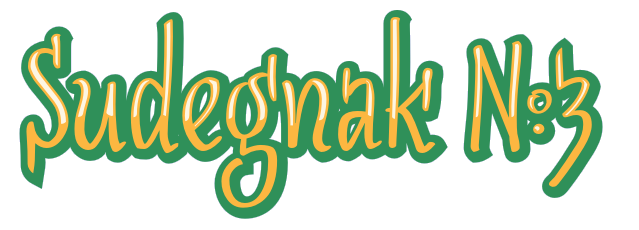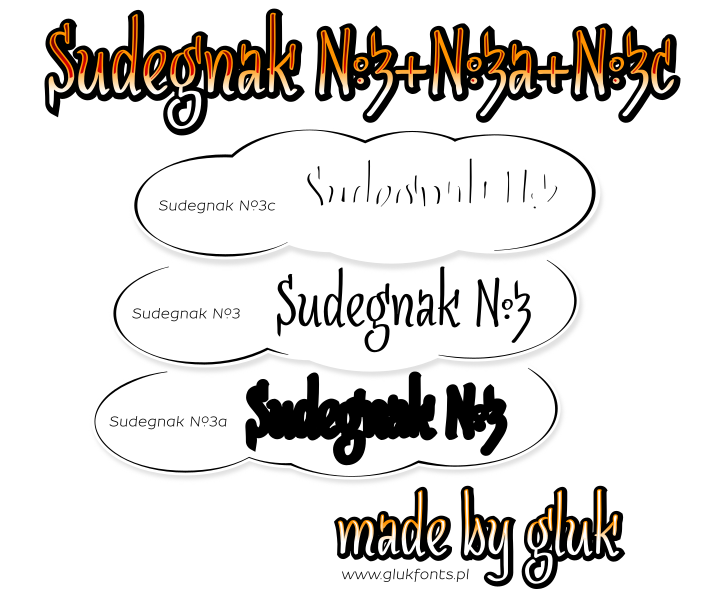
Schrift mit integriertem Hintergrund (oder kräftiges Outline) für gute Lesbarkeit auf verschiedenen Hintergründen?
Ich suche eine Schriftart, die Ich in einer Bildbearbeitung ohne der Möglichkeit des aktivierens von Hintergrund ("Marker") einsetzen kann.
Vor verschiedenen Hintergründen. Z.B. ein "Bild" (Raum), wo ein Pixel ein cm ist, liegt ein Teppich im Raum (Draufsicht in den Raum).
Z.B. ein creme-Gelb-Brauner Orient-Teppich Da finde Ich keine Farbe, am ehesten noch reines Gelb.
Eine für geringe Auflösungen gut lesbare Schrift inkl. eingebautem Hintergrund wäre eine Lösung.
Was gibt es da? Auch Freie?
Wenn möglich, inkl. eckigen Klammern, diesen Pfeil-Dreiecken etc.. Aber notfalls nehme Ich diese Symbole aus einer anderen Schriftart.
So etwas gibt es als Schrift überhaupt nicht, da normale Schrift-Fonts ja nur die Außenkontur der einzelnen Glyphen beschreiben, die dann von der Anwendung mit der gewünschten Farbe gefüllt werden. Viele Grafikprogramme bieten jedoch die Möglichkeit, der Schriftart auch eine Kontur, oder auch ein Füllung zuzuweisen. Das ist aber keine Sache der Schrift.
seit Windows8 hat Microsoft ein neues Font-Format für Emojis eingeführt, hier sind farbig definierte Schriften durchaus möglich, da hier Microsoft einem Aufsatz auf das vorhandene OpenType-Format mit einer neuen OpenType-Table gemacht hat, indem zur Grundglyphe, die in Anwendungen ohne Farb-Unterstützung (also der großen Mehrzahl an Text- und Grafikprogrammen) dann dargestellt wird (in schwarz oder einer gewählten Schriftfarbe) und weiteren Sub-Glyphen, denen schon ein rgb-Farbwert zugewiesen ist. Quasi eine Layer-Schrift in einem Font. Allerdings werden diese Emoji-Farb-Fonts nur in Microsoft-Chat-Apps für Emojis eingesetzt.
Apple ist da einen inkompatiblen anderen Weg gegangen, hier wurden für die farbigen Bildchen kleine PNG-Pixelbilder im Spezialfont hinterlegt, das begrenzt natürlich die Darstellungsgröße,
erlaubt aber Farbverläufe und natürliche Schattierungen.
In normalen Schriften und nahezu allen Grafikprogrammen geht da nur der Weg über einen Layer-Font-Set. der erste Font ist dann für die unterste Ebene, dann kopiert man den Text und fügt ihn über dem ersten erneut ein, gibt den Text eine andere Farbe und wechselt zur Schriftart der 2. Ebene und so fort ...
Catfonts wies schon auf die sgg. Multi-Layer-Schriften hin. Damit Du dies Dir besser vorstellen und auch selber ausprobieren kannst liefer ich Dir hier als Beispiel die freie Schrift (Public Domain/GPL/OFL) Sudegnak No 3 von gluk:
Damit kannst Du ausprobieren wie dieses Verfahren geht. Leider kenne ich keine andere freie Multilayerschrift mit der dies auch so ginge. Eine weitere Alternative ist eine Kopie des Originaltextes, vektorisieren und erweiteren/verfetten (entspricht Sudegnak Nr 3a) und diese dann unter den Originalschrift zu legen. Bei jeder Änderung im Text muss man diesen Untergrund jedoch neu anlegen, bei Multi-Layer-Schriften nur den Text in beiden Schriftzügen ändern. Nun solltest Du wissen nach was Du zu suchen hast, so Du Dich für Multi-Layer-Schriften entscheidest.
Und bei einer GPL/OFL-Schrift ohne Outline könnte man diese auch mit einem Fonteditor selber schnitzen.
Wenn man dann das Fetten in Fontlab 5.x macht, darauf achten, dass sich die Metriks des Fonts nicht ändern.actions.jpg
Hierzu darf die leicht missverständliche Wahlmöglichkeit im Fetten-Dialog "Keep glyph dimension" NICHT ausgewählt werden, da sonst Fontlab die gefettete Glyphe so weit verkleinert, bis die x-Höhe wieder der der ungefetteten entspricht, Hierdurch ändert sich aber auch die Laufweite der Schrift und die so gefettete Version taugt nicht als Layer.
Wie das in Fontforge, Fontographer, FontCreator, Glyphs oder Fontlab VI geht, kann ich jetzt nicht sagen
andere freie Multilayerschrift mit der dies auch so ginge
Hier sind noch ein paar. Oder meintest du jetzt was anderes? :-?
Im Rahmen eines kleinen Vorabtestlauf zu freien Multilayerschriften habe ich u. a. die Villa Didot in der Mangel gehabt ...